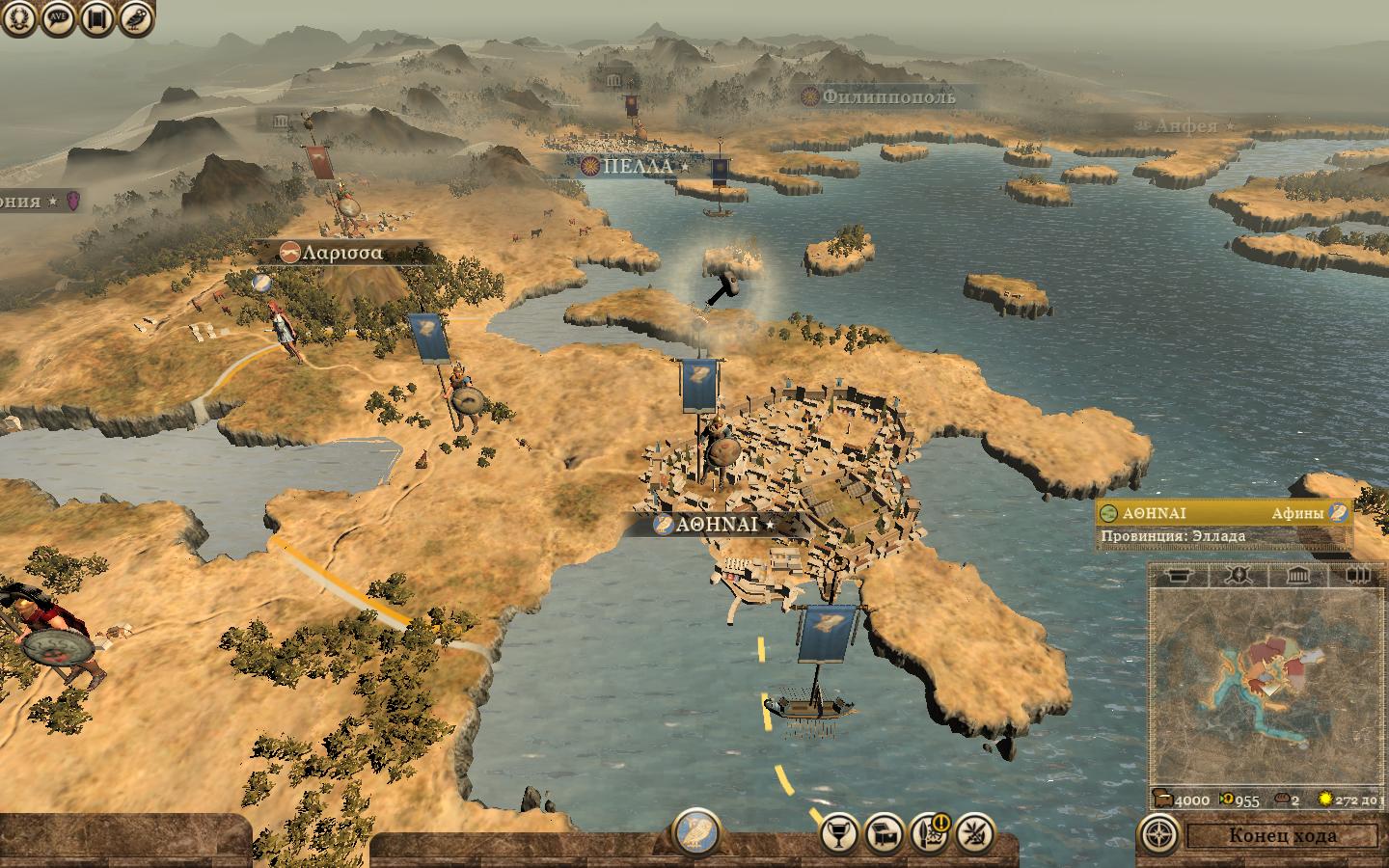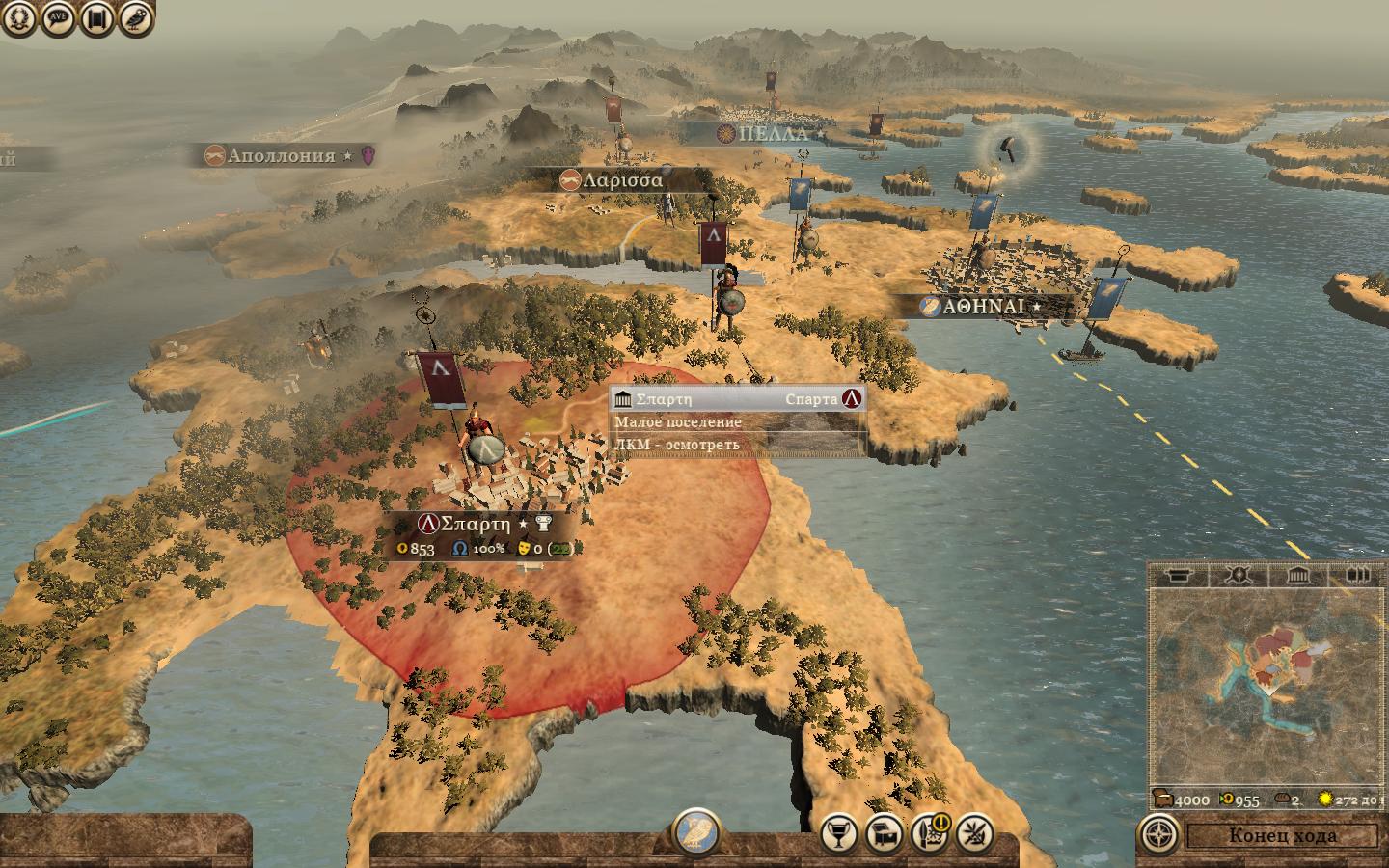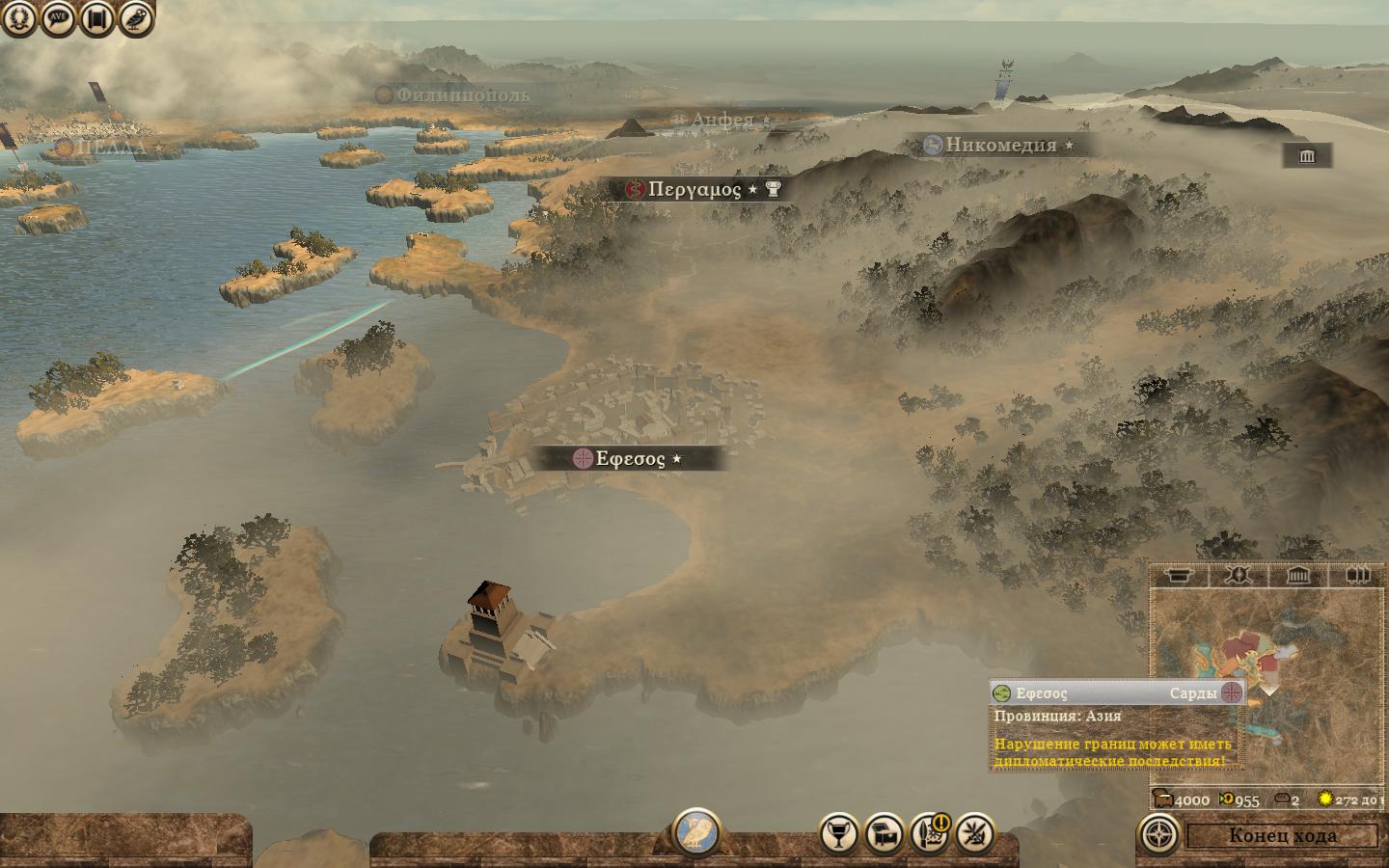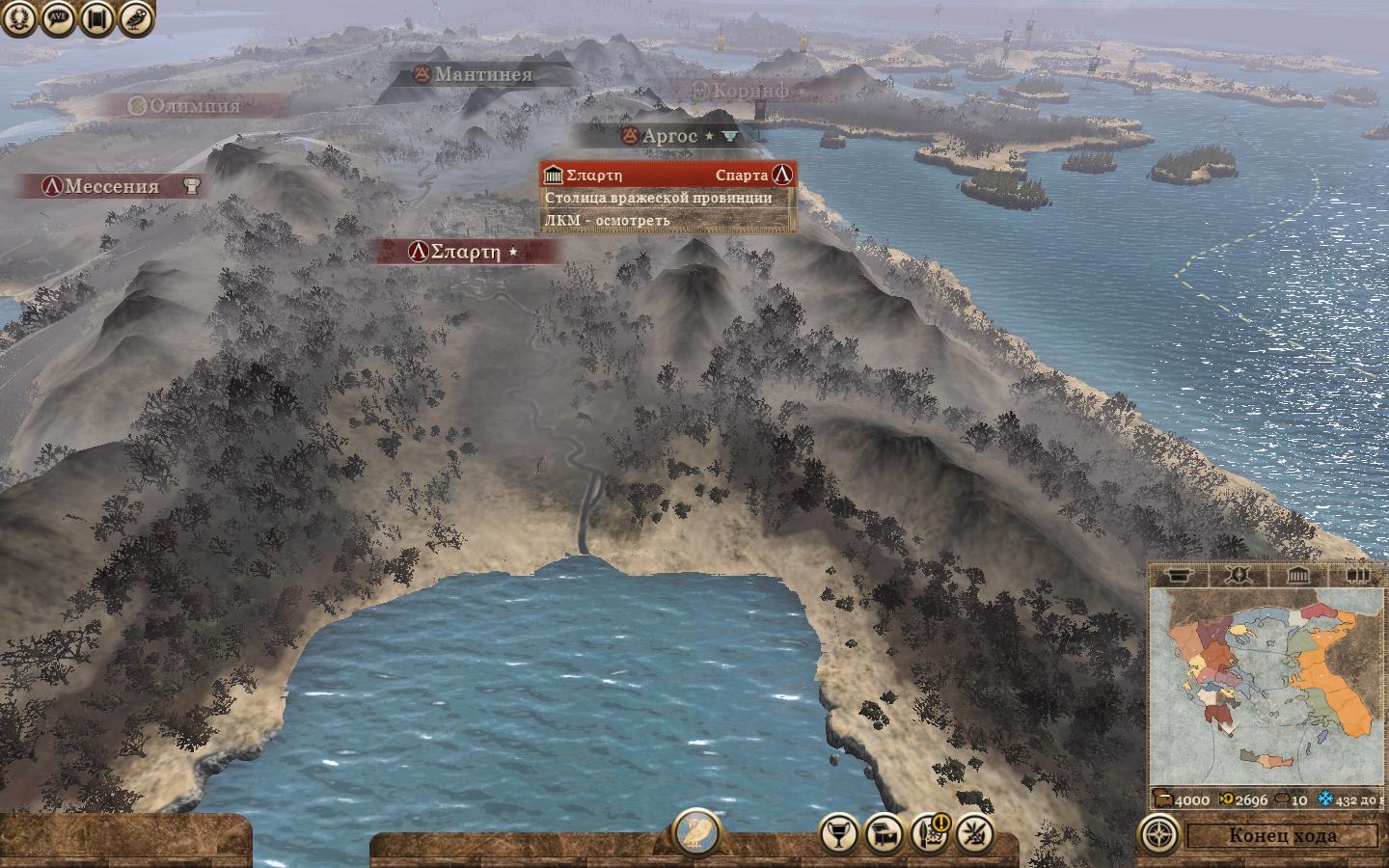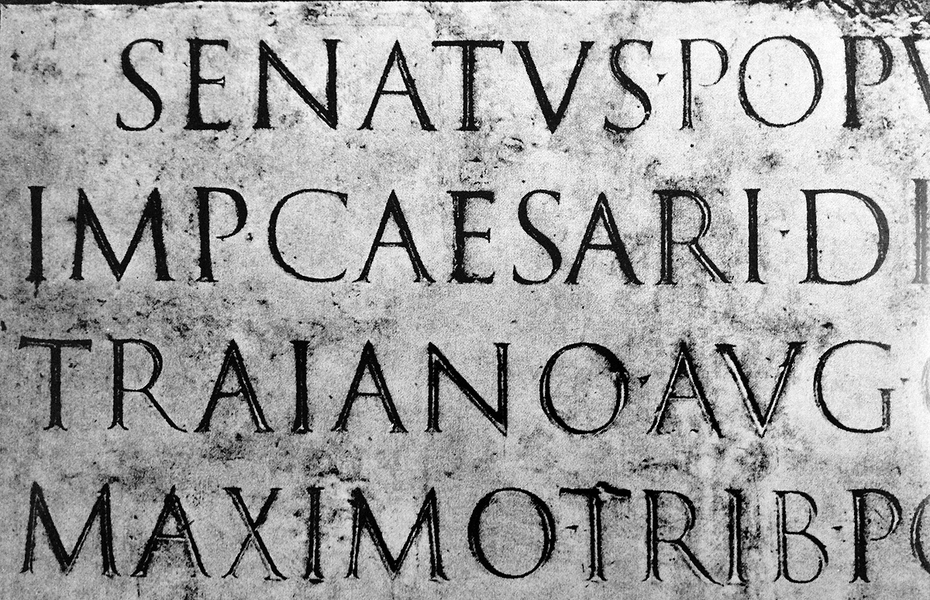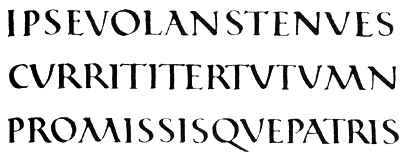
Универсальные шрифты для Total War: Rome II
Шрифты для ATW и TWR2. Можно использовать в качестве саб-модов
Саб-моды на шрифты изготовлены мной и идентичных не существует. То есть этот проект - детище "Империала".
На вопросы, подобные, таким как: сделай шире-уже, выше-ниже, и так далее, отвечу заранее и больше не буду, так как, ответ один - на данный момент возможности инструментария и не желание СА, ограничивают возможность делать вещи. Перед вами самые оптимальные варианты. Пока так. По мере возможности, постараюсь, что-то добавлять... По остальным вопросам - пожалуйста.
Греческий:
Римский:
Готический:
В Аттиле, кстати, константиновский шрифт выглядит не так хорошо: в ряде мест буквы (и цифры на характеристиках отрядов) обрезаются по горизонтали, в других (загрузочные экраны) — по вертикали. Видимо для Аттилы нужен шрифт покомпактнее.
Есть такое дело... :0182: Хочется что-бы читалось без напряга - не влезает, всё влезает - глаза рвёт. Золотая середина для Рима и Аттилы - редкость, как, видно... Если честно - аттиловские тексты очень длинные, подлежат,обрезке. Да и появляются они только при загрузке игры. В принципе, текст, правится - выловить что именно и изменить... :008:
А можете, допустим, сделать шрифт под рабочим названием Atilla Total War, вырезав буквы из стратегической карты?
Вырежьте, что нужно, запакуйте в формат ttf. А я сделаю саб-мод изменяющий ванильный шрифт на ваш... :008:
Старый свой мод я удалил, да он и не подойдет сейчас, поэтому сделал по-быстрому на основе локализации Савромата. Афины написаны прописными буквами, как и Пелла, Большая компания:
Гнев Спарты:
И вам здрасте! Прикольно смотрится... Для знатоков, думаю, бесценно было бы играть в таком стиле оформления. :006:
То есть вы можете написать название римских городов в таком стиле:
А как это сделать? И уточните про шрифты: где лежат и как называются... :038:
С римскими городами бесполезно, т.к. разницы нет. Римляне просто пробелов не ставили, вот и все. С греческими я тоже все уже сделал, хотя бы в прошлый раз. Есть смысл то же самое попытаться сделать с восточными городами, чтобы названия восточных городов было на арамейском, т.е. написано ивритом.
Соряныч конечно за возможный оффтоп, но есть ли вариант как-то приспособить готический шрифт(первый вариант) для Мед2? Уж куда-куда, а туда он(шрифт) прямо таки просится. Все таки в Меди2 имхо он более органично будет смотреться нежели в античных реалиях второго Рима..
Изначально инструментарий и заточен был под Медь :0142: А можно или нельзя - не ведаю... Последний раз руссификацией на DBM занимался года эдак три назад... :046: И насколько помню - постоянно с текстом на русском беда была.Требовалось удаление папки font...